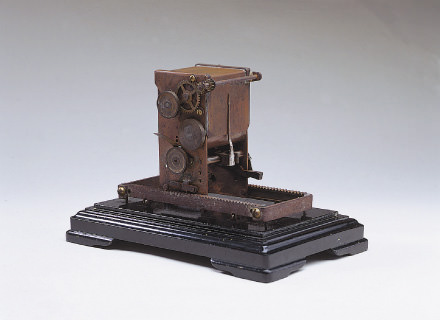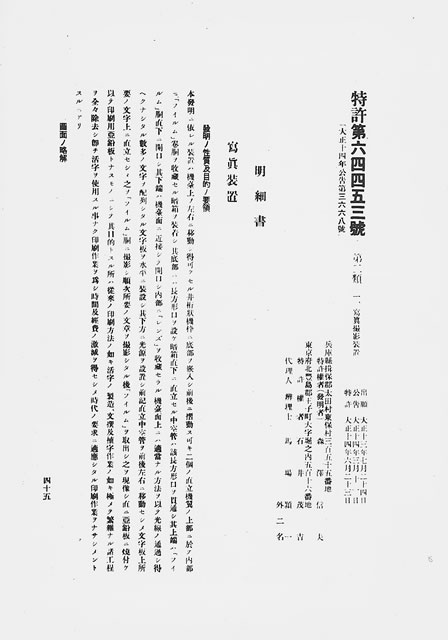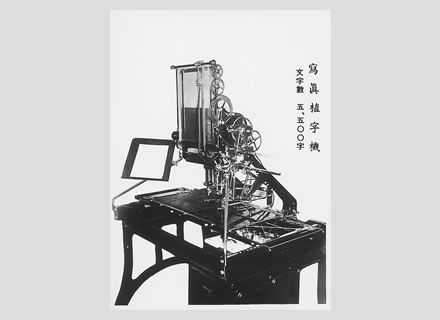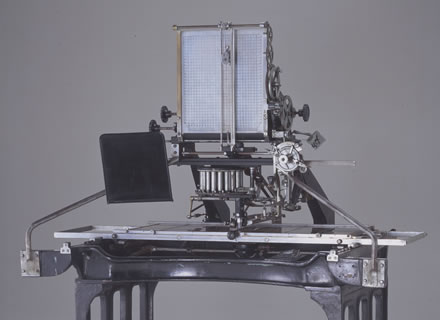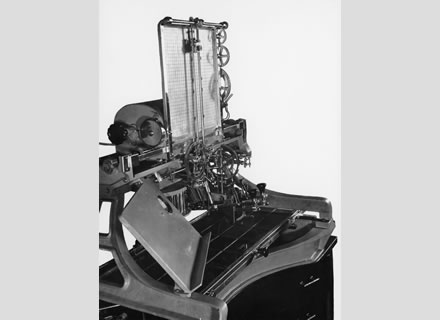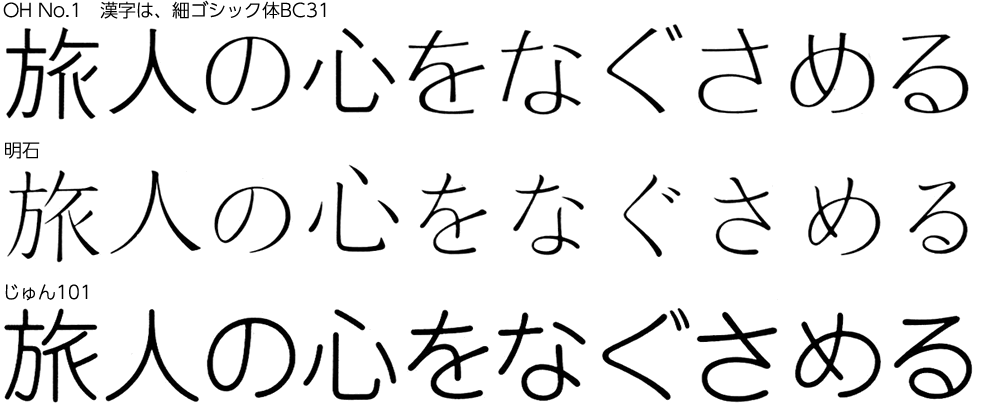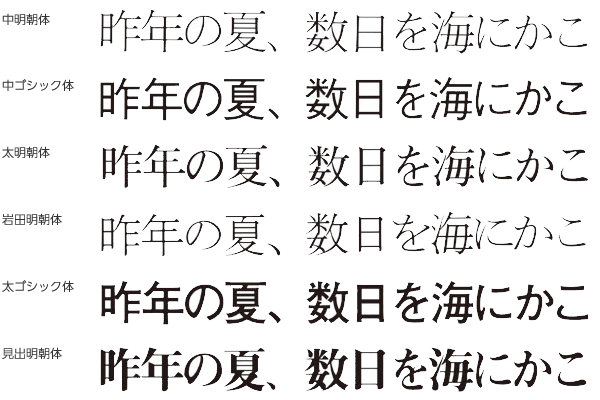
歴史・沿革
7月24日、森澤信夫が世界に先駆けて「邦文写真植字機」を発明。
森澤信夫は星製薬在籍時、活字を組むという煩雑な仕事に悩んでいたある日、イギリスで「写真で字を組む機械」を開発中だがなかなか実用化できないという情報を聞いてこの方法に特別な関心をいだき、自分もその研究に取り憑かれていった。そして1924年7月、遂に写真の原理で文字を現して組む方法を世界に先駆けて考案し、その発明模型を「邦文写真植字機」と名付けて特許を申請した。発明のきっかけは、アルファベット活字は字によって幅が異なるが、日本語活字は漢字、かな、すべて「四角」だ、だから1字写すたびにフィルムを1字分だけ移動させればよい、ということに気がついたからであった。
星製薬時代の森澤信夫(23歳)
邦文写真植字機の発明模型(本社内に保存展示)
石井茂吉氏らと試作機の製作に取り組む。
特許は6月に「写真装置」という名称で許可され、この構想を事業化するため森澤は、星一社長の援助と、同僚の⽯井茂吉⽒ら3名の協力者を得て試作機の製作に取り組んだ。
「写真装置」として特許公示。特許権者(発明者)森澤信夫と明記された。
森澤と石井氏は 試作機の改良を重ねながら共同事業者としての契約を交わし、1926年に現在の東京都北区堀船町に平屋建て工場を設立、「写真植字機研究所」という看板を掲げて実用化を目指した。
写真植字機研究所
待望の実用写真植字機が完成。
10月、待望の実用写真植字機第1号機が完成、文字盤に収容する字数は明朝体5,460字であった。同機は東西五大印刷会社に1台ずつ納入されたが、当時はまだオフセット印刷の時代ではなくほとんど稼働しなかった。
実用写真植字機第1号機
⽯井⽒との共同事業を解消して森澤は帰阪し、浪速区で写真植字製版業を開業した。その後翌年からは⻄成区津守で螺⼦⼯場を設⽴、その製造だけでなく機器の改良、発明にも成功して終戦を迎えた。
終戦後、石井氏との共同事業を再開。大阪で「A型機」を製造。
戦後、⽯井⽒からの要請で、共同事業を再提携したいという願い出に応じ森澤は再度、写植機開発に携わることを決断した。契約は森澤が大阪で写植機の本体を製造して東京に送り、石井氏がこれにレンズ、電気部品を取り付けて販売するというものであった。森澤が大阪市西成区北津守3丁目に工場を借りて製造したこの当時の写植機は後に「A型」と命名され、1949年にかけて約100台が販売された。
1946年当時の「A型」
「写真植字機製作株式会社」を設立。組版機構を抜本的に改革した「MC型」を発表。
森澤は工場を西成区津守町691に移転、資本金100万円の法人組織に改め、商号を「写真植字機製作株式会社」とした。
森澤は組版精度を安定させるため、発明当時からの光源部を動かす方式をやめ、機械の心臓部である光源部は固定して、感光材・暗箱を移動させる方式に大変革し、「A型」とは機構の根本的に異なる万能型写真植字機「MC型」を完成させた。森澤の「M」とこの完成に至るまでの森澤の3度の大きな変遷を意味する「C」を名称にした。
(MC:A型の9,555⽂字に対して実⽤頻度の⾼い7,644⽂字とした。)
写真植字機製作株式会社
MC型(1949年)
開花期迎えた写真植字機、平凡社がMC型で世界大百科事典を刊行。
平凡社の下中弥三郎社長が写真植字とオフセットという画期的な方式で「世界大百科事典」全33巻を刊行するという大型構想を発表、この組版のためにMC-Ⅱ型写植機が一挙に13台東京印書館に納入された。
横組み主体の辞典類は、日本語の縦組みを主体に考えられた従来機では対応しきれない。縦、横、同等に組版できるMC型の出現は、それまでの写植の利用に対する考え方を一変させた。
「株式会社モリサワ写真植字機製作所」と改称、東京営業所を開設して独立。
大手新聞社への納入実績、出版社や学会からの高い評価を得た新機種MC型を主力機種にして販売すべきという森澤と、従来機の改造型SKを自家生産したいという石井氏との⽅向性の違いから、森澤は写真植字機研究所から独立して、商号も「株式会社モリサワ写真植字機製作所」と改称した。翌1955年には東京日本橋に東京営業所を開設、生産と販売を一貫して行う独立した企業を目指した。
モリサワのオリジナル文字盤も次々と発表。
石井氏との共同事業を解消して独立企業として歩み出した森澤は独自の書体製作にも心血を注いだ。そして、1955年、モリサワ写真植字機書体文字の第1号として「中明朝体AB1」「中ゴシック体BB1」のモリサワオリジナルの文字盤を発表。以降、1962年までに「見出明朝体」「見出ゴシック体」「教科書体」「隷書体」など当時の基本書体を次々と発表した。
「中明朝体AB1」の文字盤。かな類と最も使用頻度の高い漢字を収容しているNo.1の部分
現在地、浪速区敷津町に本社工場を移転。
本社工場を大阪市西成区津守から現在の浪速区敷津町2-5の新築社屋に移転。
浪速区敷津町の新社屋
欧文専用写真植字機を発表、ユニークな機構で18カ国で特許を取得。
森澤は、欧米でも解決がつかないでいた文字幅の異なるアルファベットを自動送りする方式を解決するためにユニークな新機構を発明して、欧文専用写真植字機「MC型」を完成させた。同機は世界18カ国で特許を取得、欧米、東南アジア、ロシア、アフリカなど世界の約60の国と地域に輸出された。
欧文専用写真植字機「MC-101型」
ピンの高低で「W」「I」のように文字幅の異なる欧文の送り歯数を調節する新機構。
文字盤製造部門を独立させ、兵庫県明石市の新社屋に移転。
東京オリンピックTV放送用にテロップ専用機を開発。
NHKの要請に応えて東京オリンピックTV放送用にテレビテロップ専用写真植字機「MD-T型」を開発した。NHKは2年前から数百万円を投資して独自に研究してきていたが、出来た機械は思わしくなかった。開会まで1年余となってしまい、そこで森澤になんとか作れないかとの緊急の依頼であった。NHKのオリンピック報道の成功に寄与した同機は、その後日本中のTV放送局に導入された。
テレビテロップ専用写真写植機「MD-T型」。特殊な印画紙を研究開発した富士フィルムの協力も大きい。
究極の万能型手動写真植字機「MC-6型」発売。
1948年の「MC-1型」から19年が経ち、使いやすさ、堅牢性など究極の万能型といえる手動写植機「MC-6型」が完成した。「MC-6型」は15年目には1万台を販売するという超ロングセラー機となった。
MC-6型
日本橋から飯田橋の新築社屋に移転、「東京支店」と改称。
東京支店が現在地の新宿区下宮比町15-5の新築社屋に移転。印刷関連業のメッカといわれる地域であり、交通の便もよいところから、印刷業界の要請に応えて開校した写植オペレータ養成講座は日中、夜間ともに盛況であった。
東京支店新社屋。
文字盤製造部門を法人化し「モリサワ文研株式会社」を設立。
森澤公雄、代表取締役社長に就任。
商号を「株式会社モリサワ」に改称、本社新社屋も完成。
商号を「株式会社モリサワ」と改称。
本社工場隣接地に地下1階地上8階の新社屋完成。
本社工場に隣接して新社屋完成
• 「OH」「明石」「じゅん」など新書体発表が続く。
「OH」「明石」「じゅん」
「写真植字機発明50周年」記念式典を開催。『写真植字機五十年』を発行。
代表取締役社長森澤信夫、代表取締役会長に就任。
取締役東京支店長森澤嘉昭、代表取締役社長に就任。
手動写植機が電子制御時代に入る。
超小型高性能コンピュータ内蔵の万能写真植字機「MC-101型」発表。
万能写真植字機「MC-101型」
自分の目で確認しながら印字ができる、写植の夢を実現した「モアビジョン」を発表。
印字した文字、採字状態をブラウン管上に映し出す写真植字機モニタ装置「モアビジョン」を発表。写真植字の世界で初めて直接肉眼で印字を確認できる装置の完成として脚光を浴びた。
印字状態をブラウン管上で確認できる「モアビジョン」
第三世代写植機の時代へ。「モリサワーライノタイプ株式会社」設立。
ライノタイプ・リミテッドとの合弁により、モリサワ本社新館内にモリサワ-ライノタイプ株式会社を設立、森澤嘉昭が代表取締役社長に就任した。モリサワ-ライノタイプ電算写植システムは、廉価で高性能、しかも、業務形態に合わせて自由にシステム構成できることから全国印刷業界に瞬く間に普及した。出力機は第三世代高速CRT写真植字機ライノトロン「202E」(日本語、漢字仕様)、入力校正機は「MK-10/MK-20/MK-50」。
ライノトロン202E
シフト式入力校正機「MK-10」
電算写真植字機ライノトロン202E対応日本語フォントがリリースされ、翌年までに基本12書体がラインナップされた。
(202:販売当初は6書体、⽂字数は⼿動機同様の7,000字であった。)
基本12書体
亀倉雄策氏デザインの新ロゴタイプを決定。
モリサワロゴ
ブラウン管上に級数、変形などの全形状を映し出すCRTディスプレイ搭載高性能万能写真植字機「ROBO-V型」
ROBO-V型
全国で盛大に「写真植字機発明60周年」記念式典。
1924年に森澤信夫が邦文写真植字機を発明してから60年目なったのを記念して「写真植字機発明60周年」記念式典、機材ショウ「MORISAWA NOW」を全国6カ所で開催。記念事業として60周年記念出版『文字の博物館』を刊行。「人間と文字」シリーズカレンダーを開始。第1回「国際タイプフェイスコンテスト・モリサワ賞」を実施するなど。
「写真植字機発明60周年」記念式典
中国の精密光学機器メーカである上海光学機械厰に最新鋭モデルである「ROBO-V型」の技術供与を行う。
中国印刷技術協会で「森澤信夫印刷奨」設立。
森澤信夫会長が中国印刷技術協会へ寄贈した奨励募金により中国で初の本格的な印刷人表彰制度「森澤信夫印刷奨」が誕生した。11月、中国・北京人民大会堂で「森澤信夫印刷奨」協議書調印式が行われた。
森澤信夫印刷奨の調印式
• 作図機能搭載・15インチCRT 超高性能写真植字機「ROBO 15XY型」
写真植字機で初めて「作図機能」を搭載した15インチCRT超高性能写真植字機「ROBO 15XY型」を発表した。
作図機能搭載・15インチCRT・超高性能写植機「ROBO 15XY型」
アドビ システムズ 株式会社(現 アドビ株式会社)と日本語ポストスクリプトフォントの共同開発、および販売契約を締結した。
MORISAWA PASSPORT for iPad
株式会社写研との協業を発表。
OpenTypeフォントの共同開発で株式会社写研と合意。
株式会社リムコーポレーションを吸収合併。
Arphic Types(台湾)を⼦会社化。
• クラウド型フォントサービス「Morisawa Fonts(モリサワフォンツ)」提供開始。
Morisawa Fonts
2022年 Morisawa Fonts
Annual license product Morisawa Fonts(2022)
写植機発明100周年を記念してMC-6型(2024)を公開。
有限会社字游工房を吸収合併。
• 2025年日本国際博覧会(大阪・関西万博)に協賛、フォントを提供。
大阪・関西万博「PRブロンズパートナー」として広報・プロモーション協賛契約を締結、会場サインなどにフォントを提供。
「大阪ヘルスケアパビリオン Nest for Reborn」と協賛契約を締結し、フォントを提供。
2025年日本国際博覧会(大阪・関西万博)
台湾事業を再編、新体制 MORISAWA ARPHIC Inc.を始動。